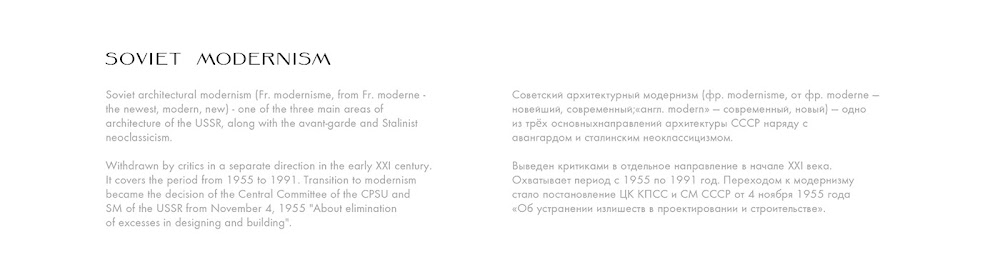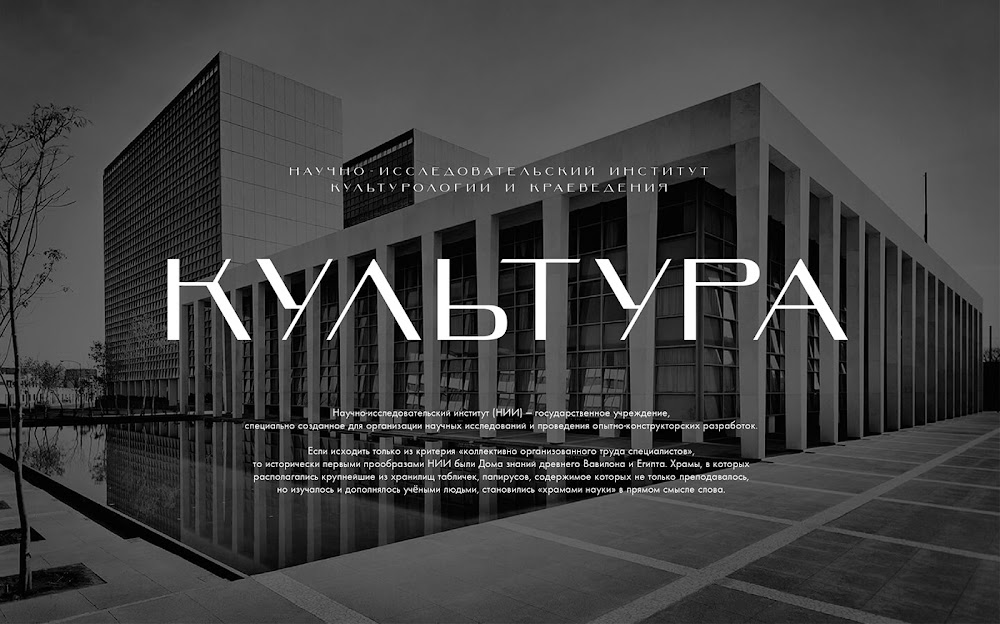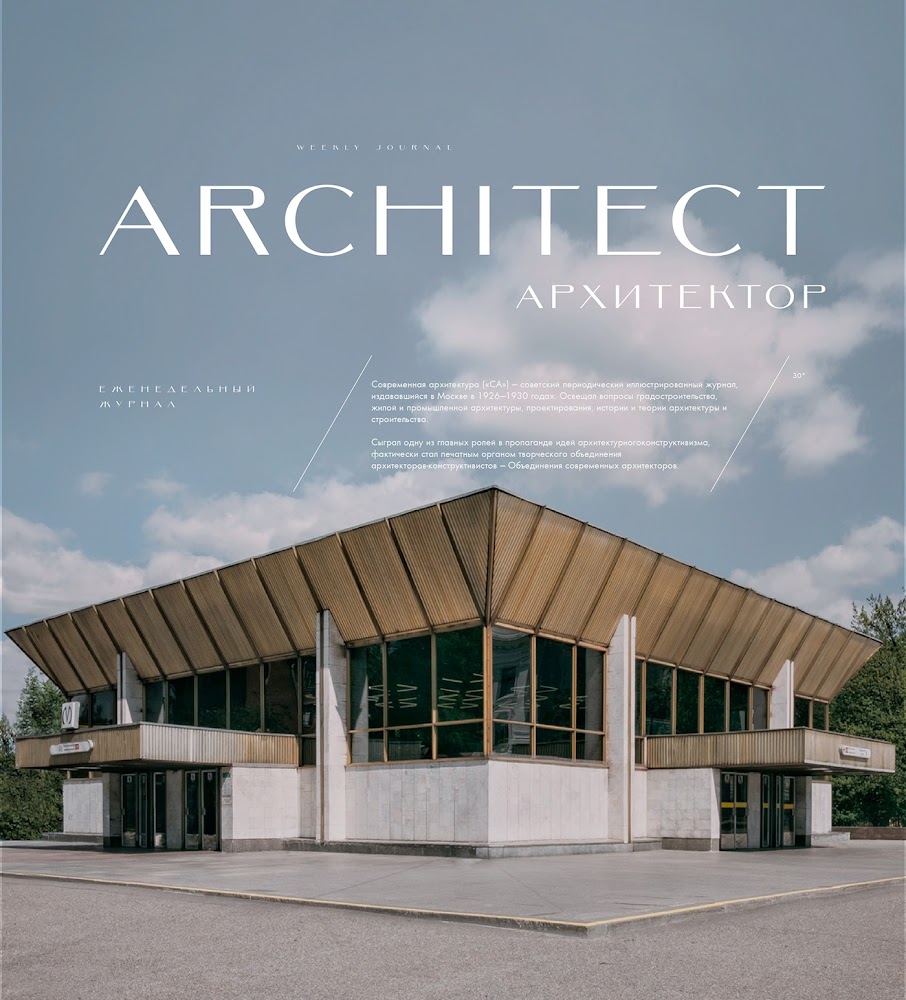
Шрифт без засечек, вдохновленный советским архитектурным модернизмом. Есть поддержка кириллицы, латиницы, всех цифр и специальных символов. Можно бесплатно использовать в личных целях. Автор Stanislav Chiganov